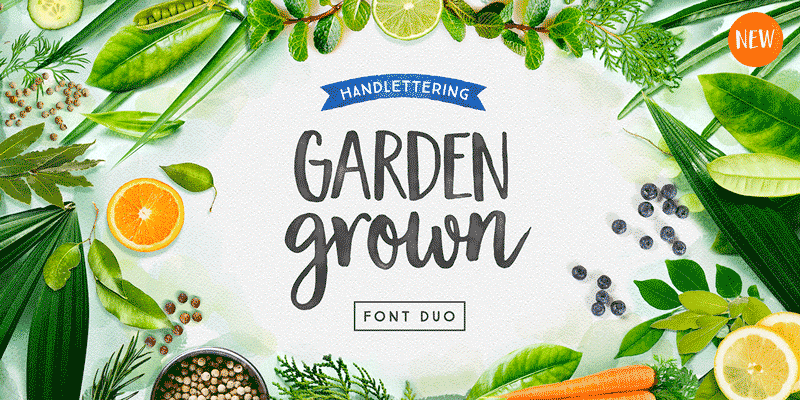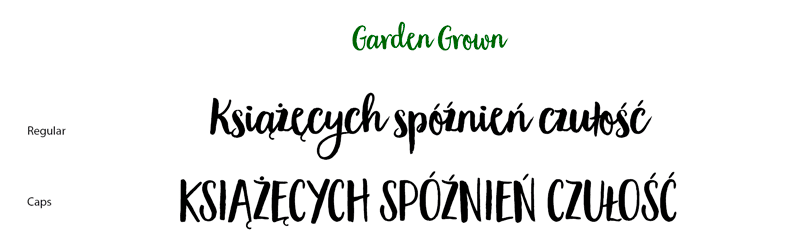
Font Garden Grown
Zakupiliśmy ozdobny font Garden Grown projektantki z Kanady, Cindy Kinash. To wesoła pisanka o swobodnym tonie nadająca się doskonale do zastosowań przy projektowaniu czasopism takich jak np. Mollie Potrafi.